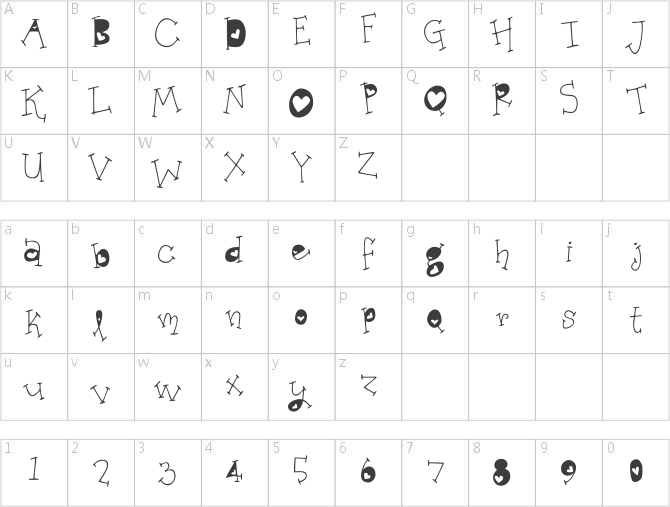
Organic-Fridays-heart-alternates 詳情頁(yè)
Organic-Fridays-heart-alternates字體字庫(kù)是一款讓人賞心悅目、百看不厭的英文字體,適合各類(lèi)廣告和產(chǎn)品包裝設(shè)計(jì)應(yīng)用,字體大小0.1MB,格式為ttf字體,上傳用戶(hù)是Bot,作者/版權(quán)方為未知